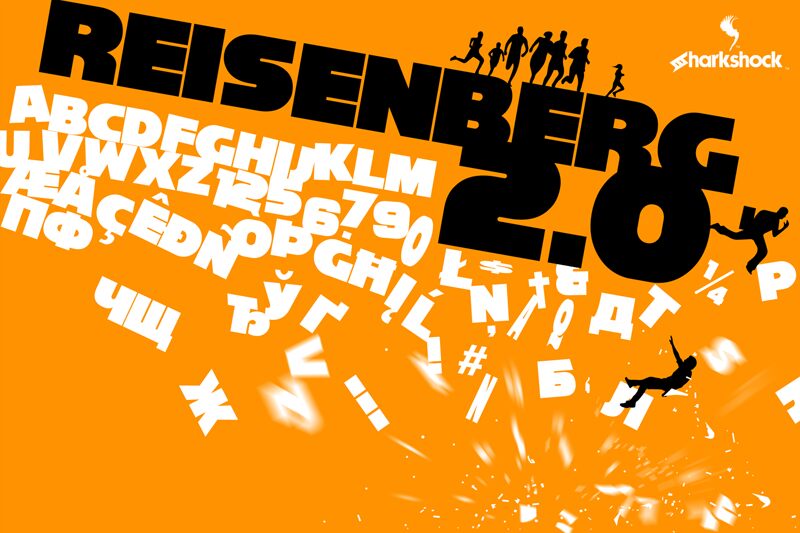
Design von Dennis Ludlow
Schnappen Sie sich den Negativraum mit der extra-dicken Reisenberg 2.0. Dieser eng laufende Klassiker wurde für die 2.0-Version überarbeitet. Diese Schriftfamilie enthält im Vergleich zum Original leicht angepasste Glyphen sowie eine neue Outlines-Variante. Die breiten, schweren Striche dieser All-Caps-Display-Schrift ziehen garantiert die Blicke auf sich und dominieren jedes Layout. Zu den Verbesserungen gehören Class-Kerning, mehr europäische Akzente, die Ergänzung von Kyrillisch sowie einige neu gezeichnete Zeichen wie das große M. Verwenden Sie Reisenberg für Filmplakate, Sport-Logos oder Medienverpackungen. Überprüfen Sie die Glyphenübersicht, um sicherzustellen, dass die benötigten Zeichen unterstützt werden. Die Demo-Version enthält grundlegende lateinische Zeichen und eine begrenzte Interpunktion.